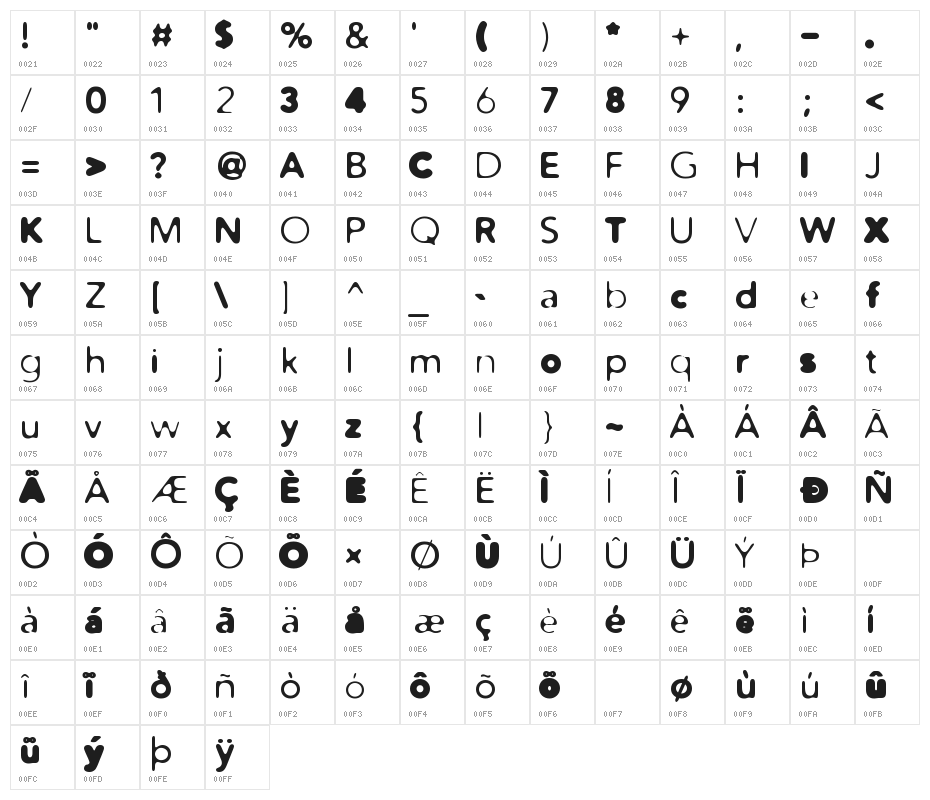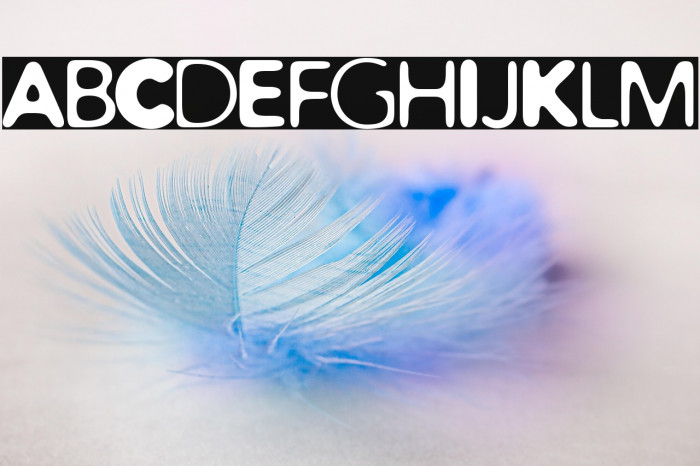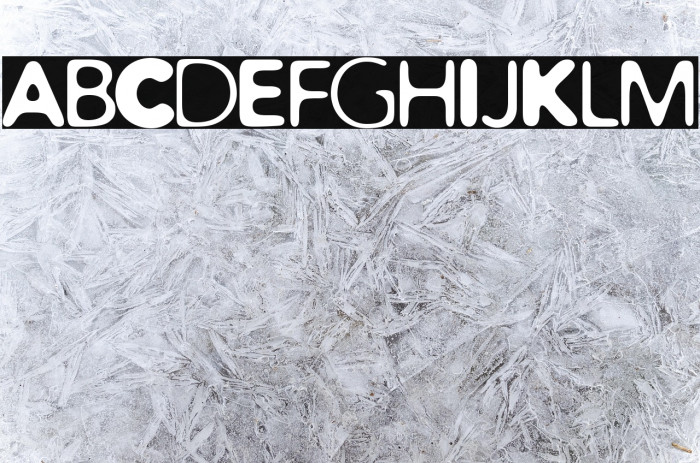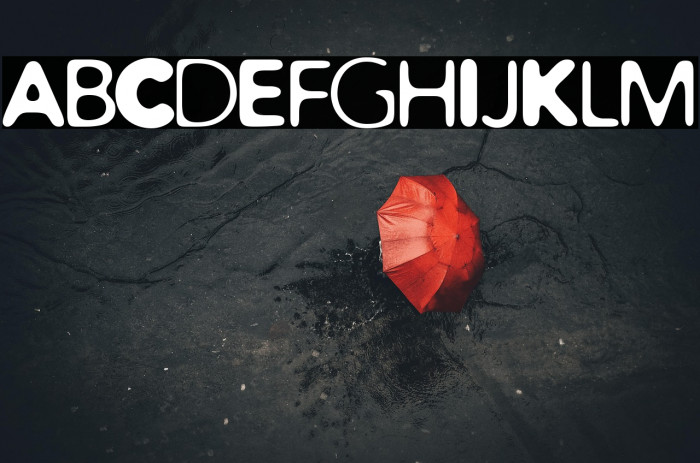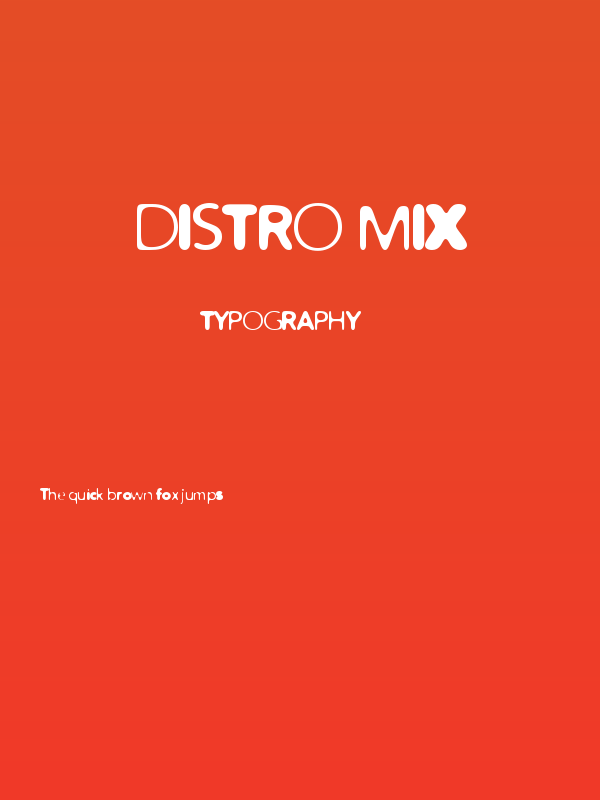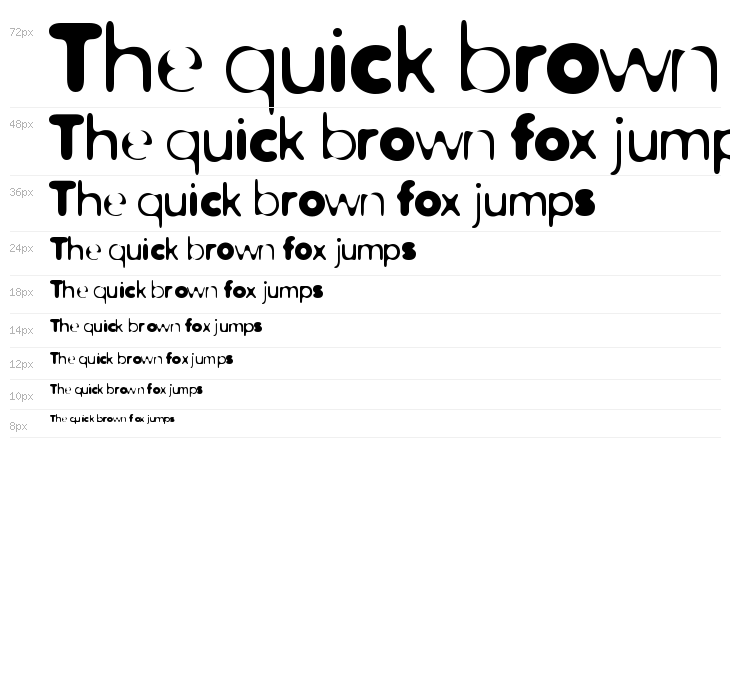
Distro Mix Font
| Stile generale | Playful, Whimsical |
| Progetti proposti | Ideal for children's books, playful branding, creative posters, and any project needing a fun, engaging look. |